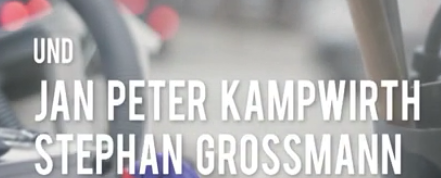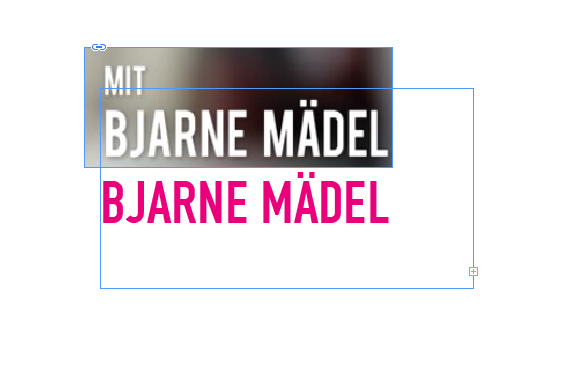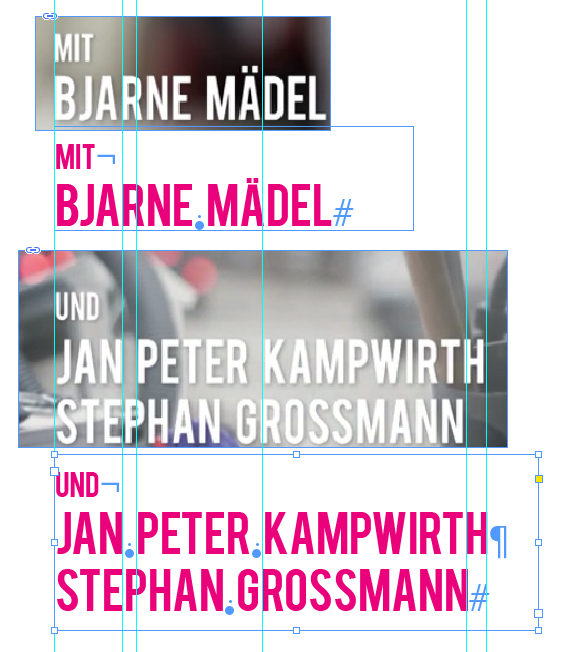
Schrift vom Vor/Abspan „Tatortreiniger"
Welche Schrift wird im Vor- und Abspan der „Tatortreinigers“ verwendet?
Die Klassiker habe ich schon relativ durch ;-)
Das G ist ein guter Anhaltspunkt/Prüfstein...
Ich weiß, meine ist auch ganz bewusst die Version "Nach Hilfsgitter gezeichnet", die etwas weniger typografisch fein ist, deshalb eben z.B. bei J und S etwas abweicht.
Ich hatte die Schrift nämlich für eine möglichst originalgetreue Erstellung von Eisenbahn-Fahrzeug-Anschriften erstellt, deren Schablonen damals nach dem Standard nicht für "Gedruckte Schrift" , sondern eben etwas vereinfacht nach der Hilfsraster-Konstruktion erstellt wurden.
So wird eben die gesuchte Schrift eine schmale fette DIN 1451 bzw. TGL 0-1451 sein, jedoch ohne die typografischen Verbesserungen der verschiedenen kommerziellen DIN-inspirierten Schriftarten.
diese oder eine sehr ähnliche Schrift habe ich auch schon mehrere Male gesehen und gesucht. Nahe an der Alternate Gothic, aber mit G ohne senkrechter Spur. Ich bin damals auch nicht fündig geworden. Auch ich habe die üblichen Verdächtigen durchsucht und bei mir war damals die ähnliches Schrift eine Alternate Gothic wegen des leicht schräg angeschnittenen S. Die Suche nach ähnlichen Schriften auf Identifont lief damals wie heute wieder ins Leere. Die Engschrift nach DIN 1451 ist IMHO weiter weg. Vielleicht klappt es hier mit der Identifikation? Wäre schön ...
Ich würde die Schrift eher in die Ecke der amerikanischen Grotesk-Schriften (American Gothic) packen. Die S-Form ist für diese Gruppe recht typisch.
Die Schrift wirkt auf mich, als wäre sie etwas in der Vertikalen verzerrt worden. Ansonsten passt sie ziemlich genau auf die Wearetrippin (Display) von Ryoichi Tsunekawa.
Irgendwie hatte ich da noch was im Kopf. Mir fiel die alte Bebas von Ryoichi Tsunekawa  (Dharmatype) ein. Diese wurde Ende 2014 als Bebas Kai komplett überarbeitet und erweitert. Die Schrift hat einige sehr ähnliche Eigenschaften und für den Einen oder die Andere sollte sie interessant sein:
Einfach mal ansehen, auch die Bebas Neue ist interessant.
Allerdings unterscheiden sich beide Schriften in einzelnen Buchstaben von den gezeigten Beispielen. Mal ist es das M und mal ist es das R ... Na ja ... einem geschenkten Gaul ...